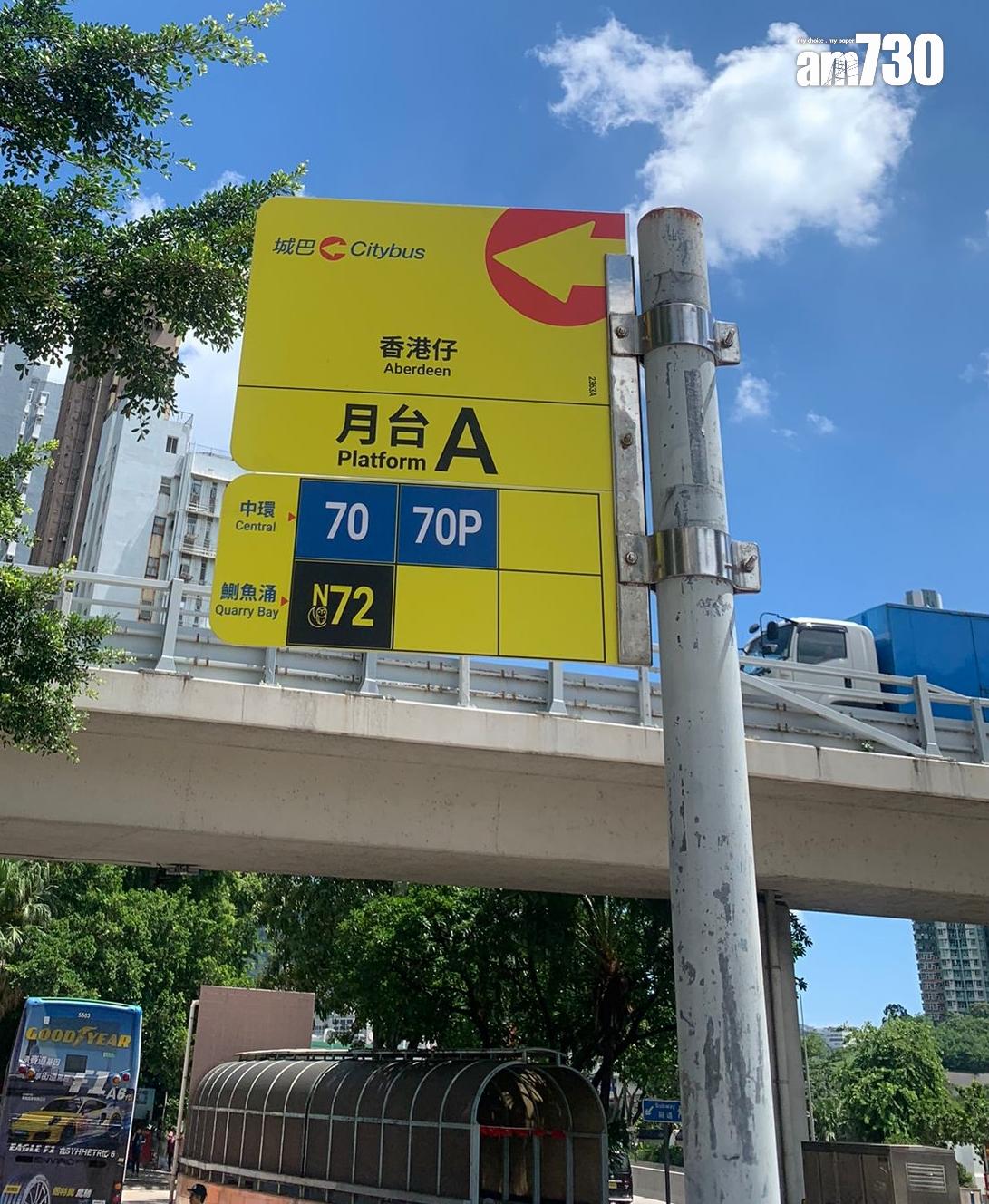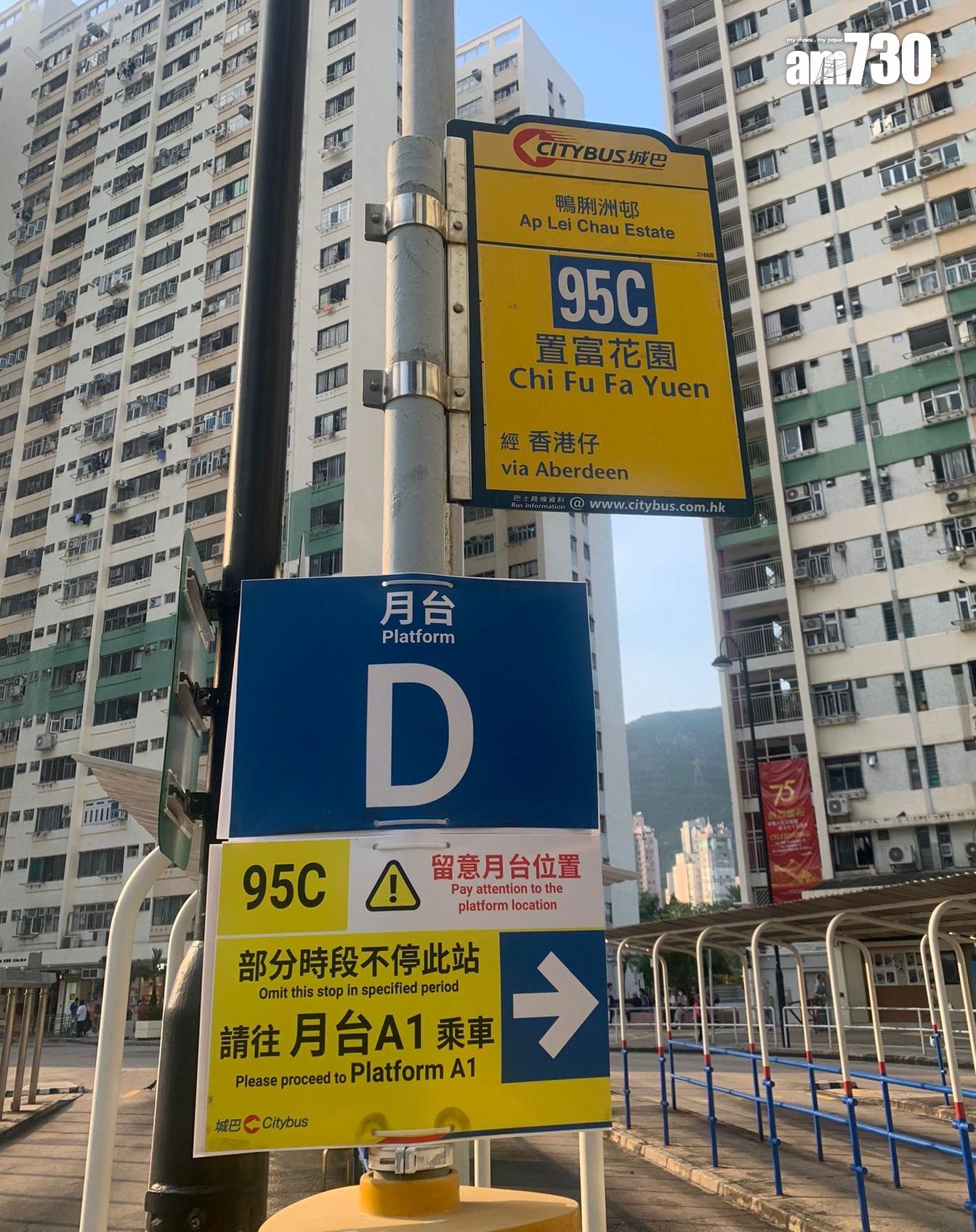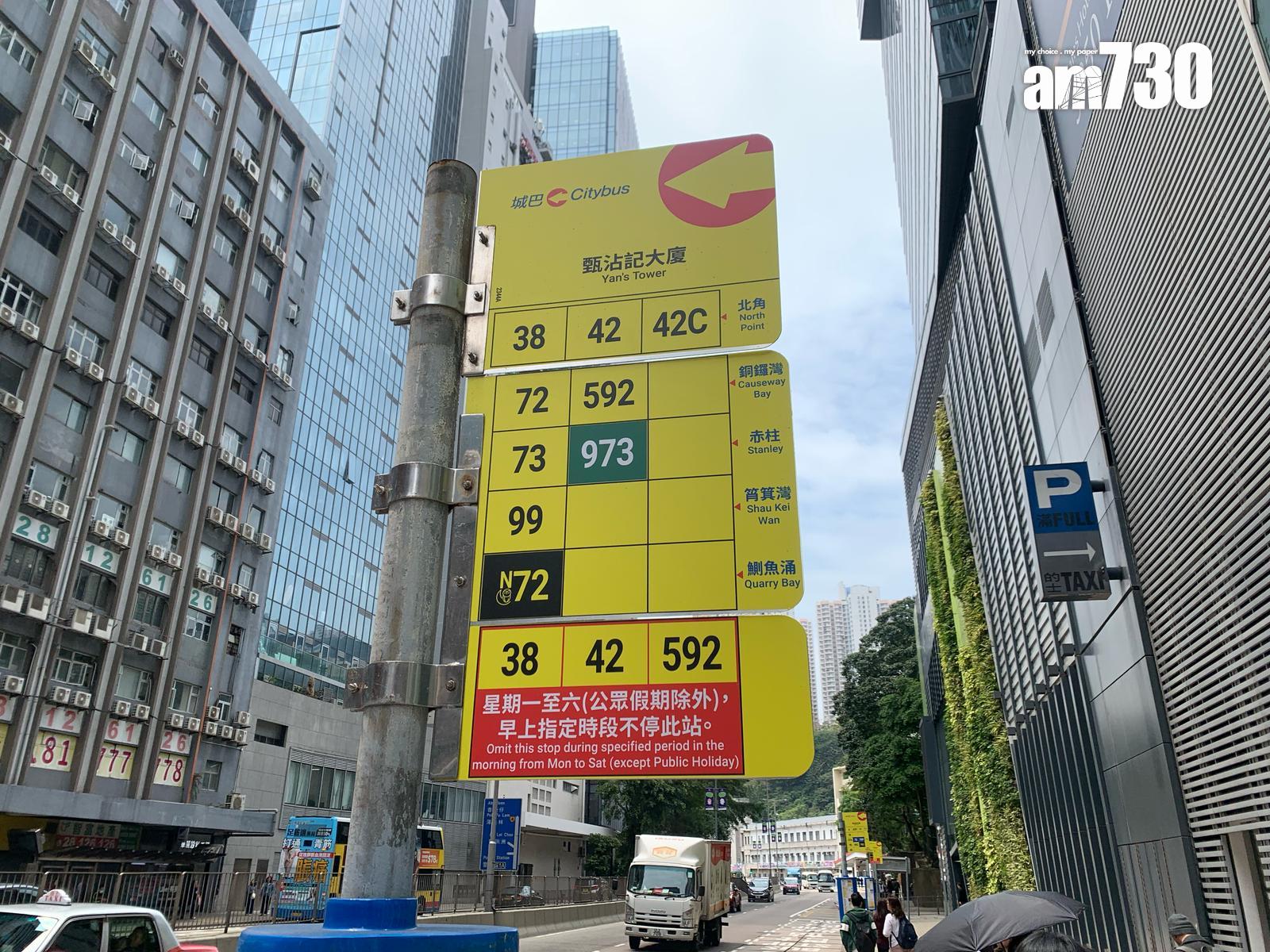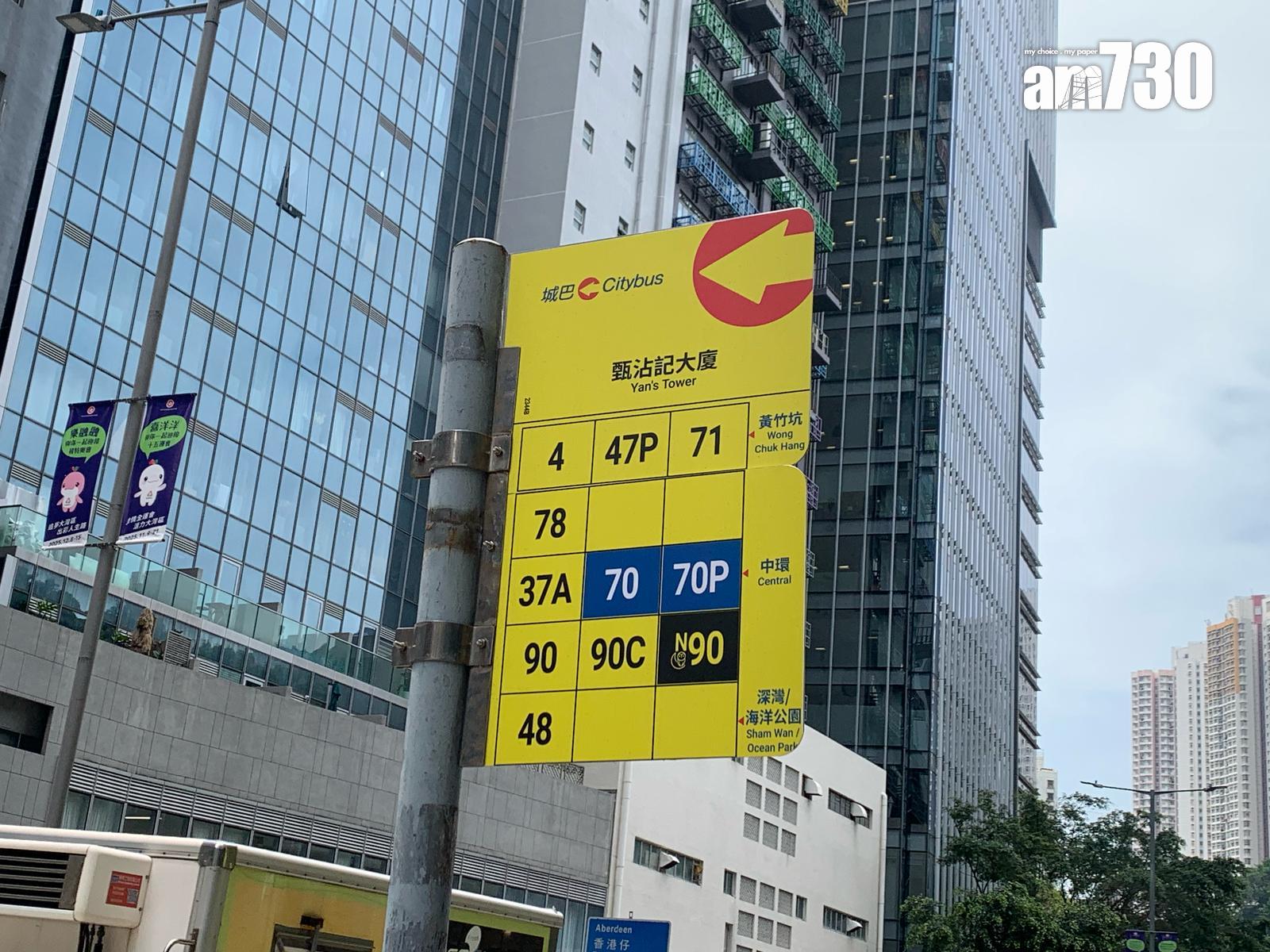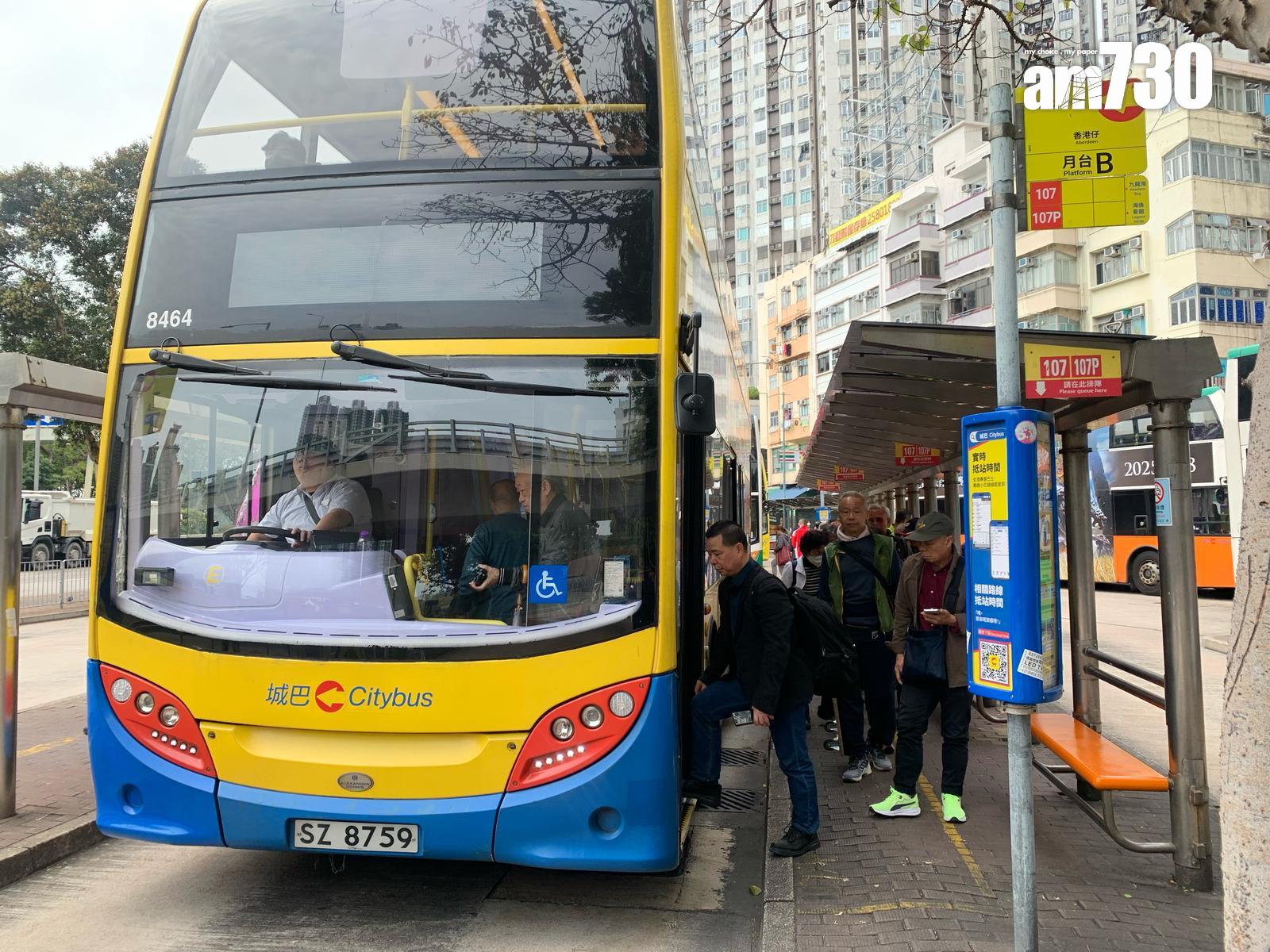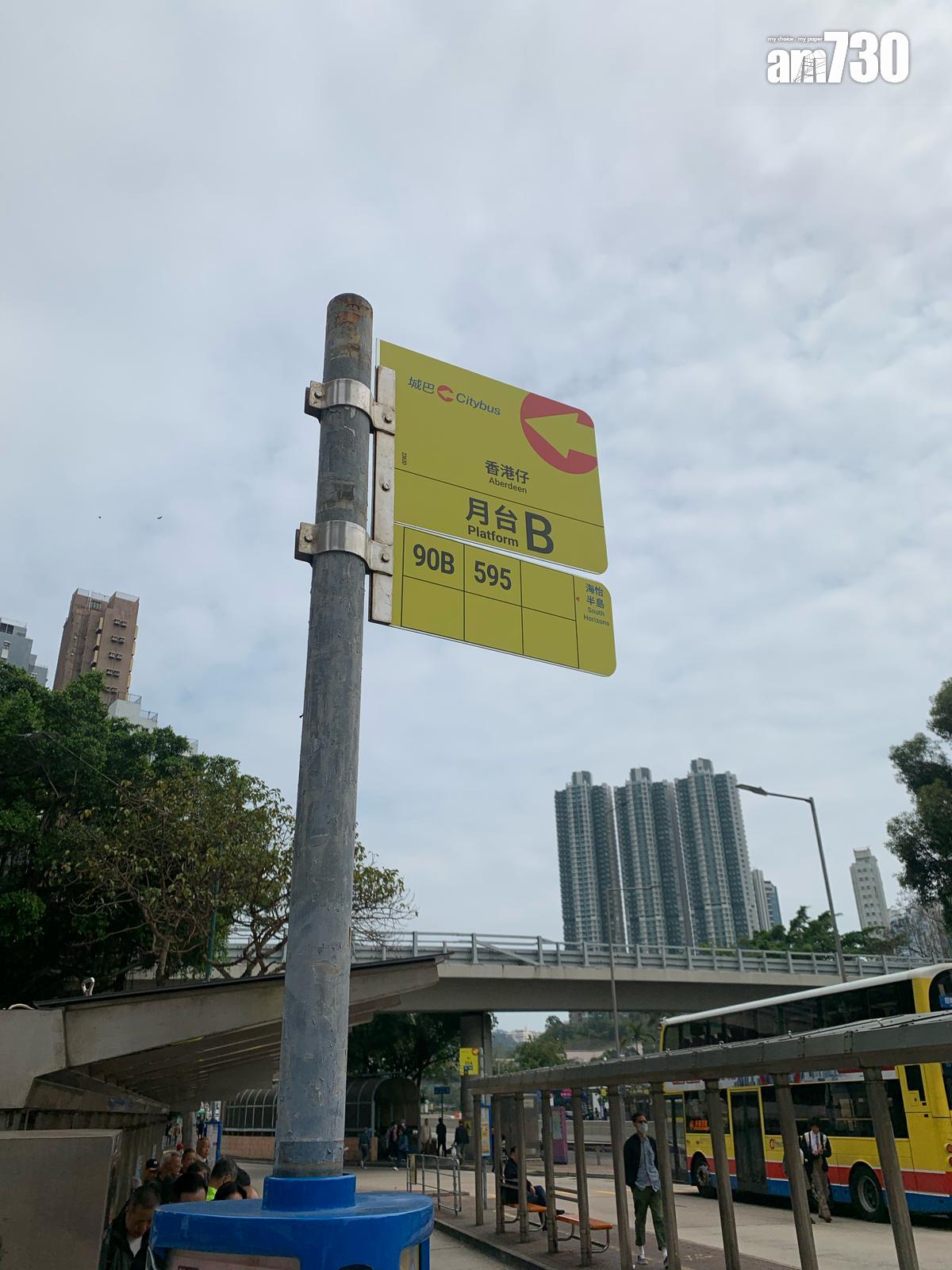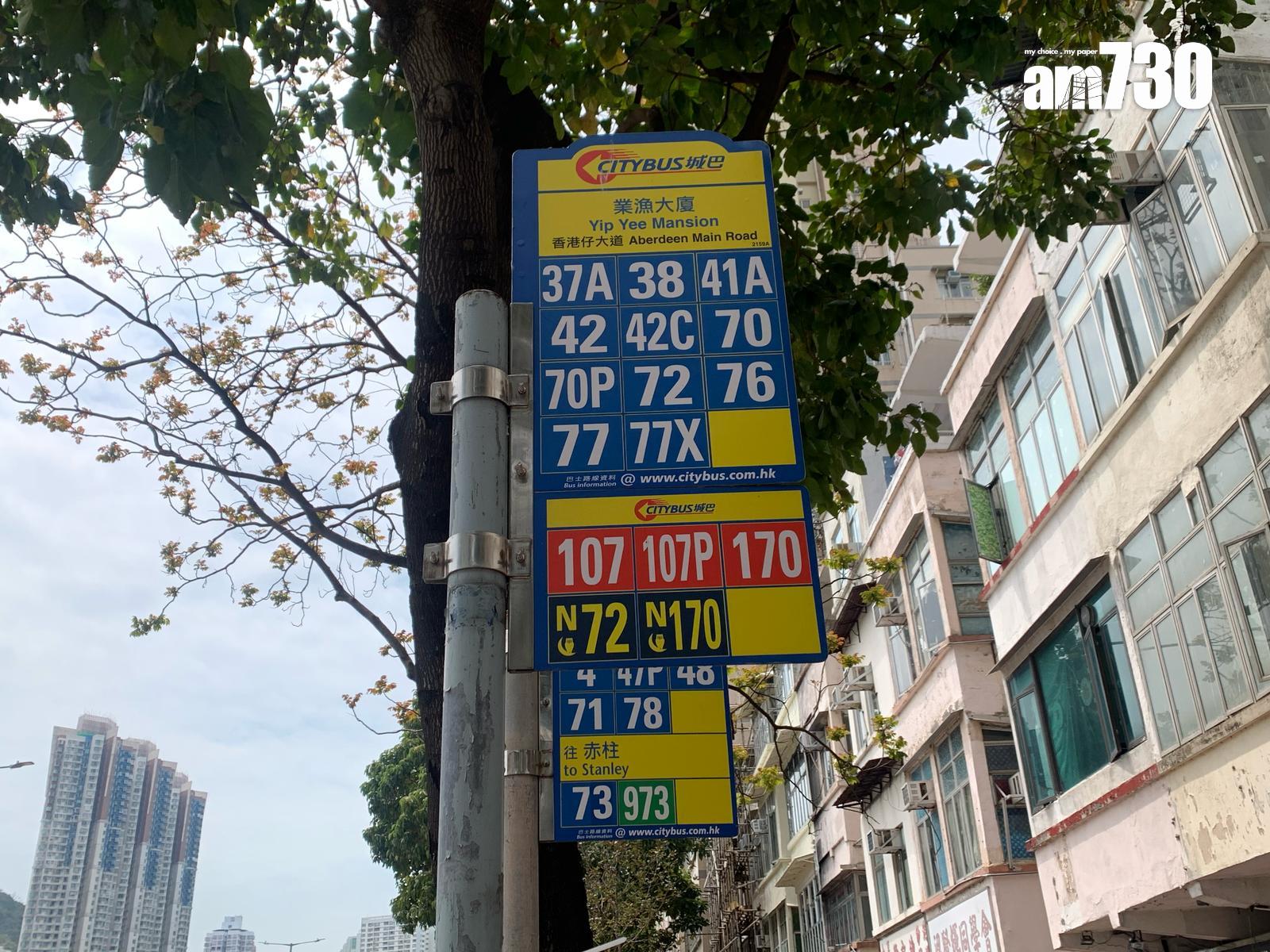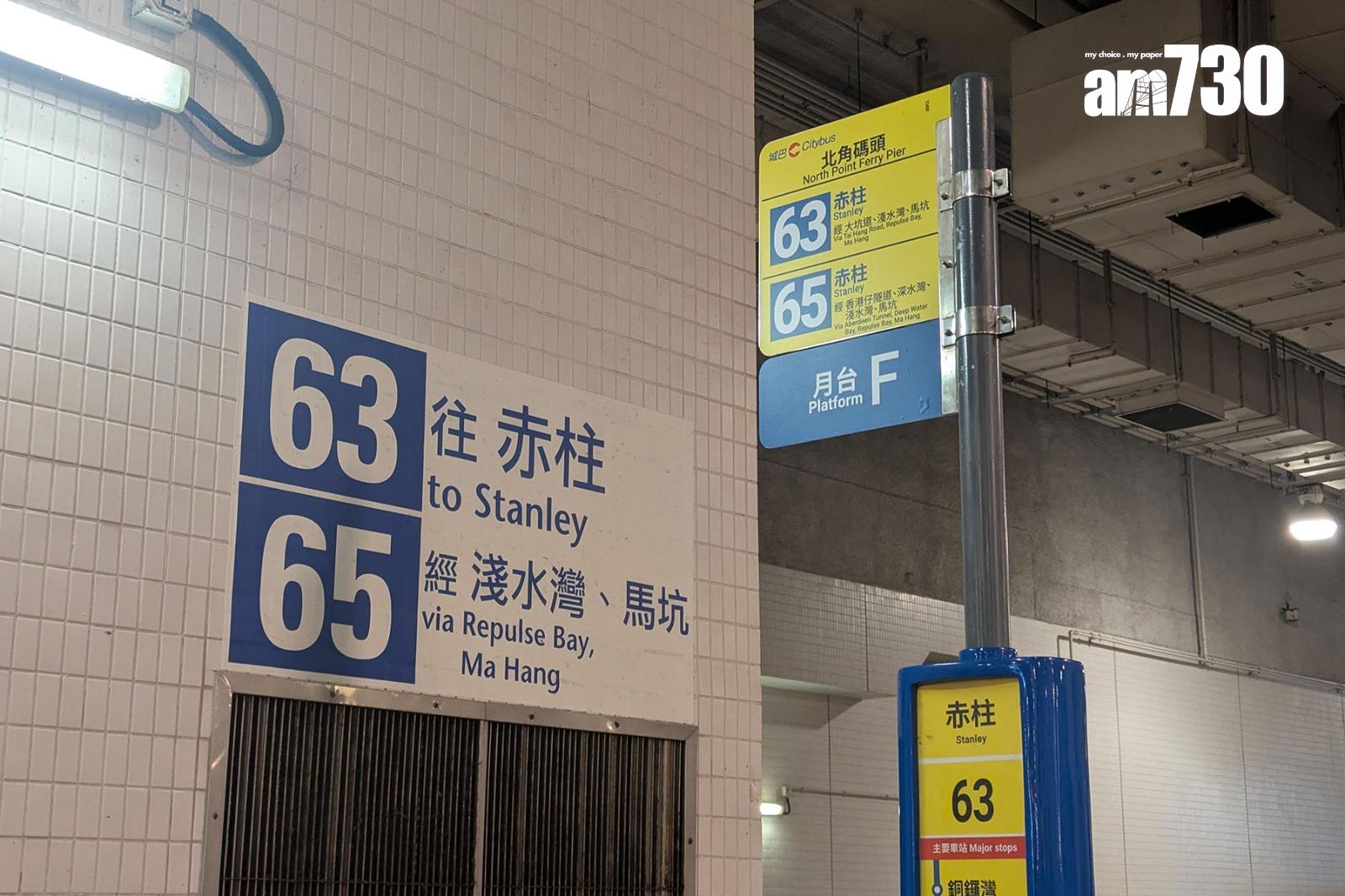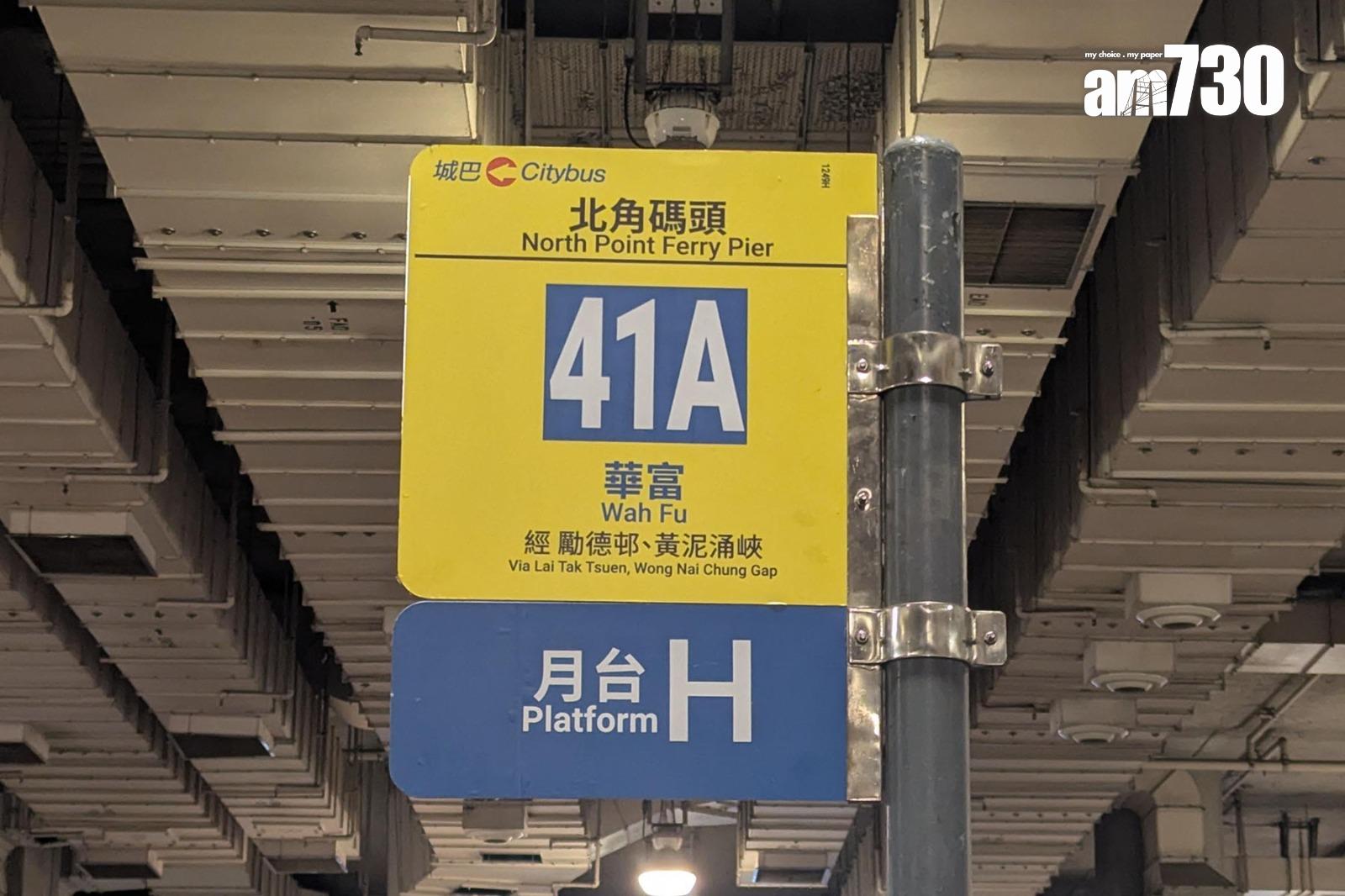
城巴更換新款巴士站牌 被批「似驗眼」後字體加大
在北角碼頭巴士總站,城巴已換上改良版新款站牌(讀者提供)
城巴去年與新巴合併後,為各區巴士站牌換上新設計,惟被指不清晰「似驗眼」影響乘客讀取路線資訊,失明人協進會接獲不少視障會員反映新設計對低視能人士做成不便,運輸署及後要求城巴改善。城巴回覆《am730》稱經諮詢相關關注團體後,已修訂巴士站牌設計,近日展開更換工程。
在北角碼頭巴士總站,城巴已換上改良版新款站牌,站牌沿用黃色設計,但對比上一款備受批評的款式,轉用較為粗身的字體,路線編號字體明顯加大,採用藍底白字粗字體,的地及途徑地點亦清晰地展示,月台編號分開擺放,不再出現月台編號比路線編號更大的設計。
城巴回覆《am730》稱自專營權合併以來,留意到乘客對巴士站牌設計有不同意見,公司持續與各持分者保持密切溝通,在諮詢相關關注團體後,城巴修訂巴士站牌設計,並於本月中旬起展開更換工程,新巴士站牌在字體大小及顏色等方面回應社會關切。
城巴為各區巴士站牌換上新設計,惟有乘客及網民均反映新站牌的路綫號碼比舊版縮細及出現「撞色」問題,難從遠方觀看,亦加了「月台」字眼更加混淆,批評設計倒退。(《am730》記者攝) 城巴為各區巴士站牌換上新設計,惟有乘客及網民均反映新站牌的路綫號碼比舊版縮細及出現「撞色」問題,難從遠方觀看,亦加了「月台」字眼更加混淆,批評設計倒退。(《am730》記者攝) 香港仔巴士總站已換上新站牌(《am730》記者攝) 城巴為各區巴士站牌換上新設計,惟有乘客及網民均反映新站牌的路綫號碼比舊版縮細及出現「撞色」問題,難從遠方觀看,亦加了「月台」字眼更加混淆,批評設計倒退。(《am730》記者攝) 有網民比較銅鑼灣希慎廣場新巴舊牌及城巴新站牌。(社交平台Threads) 城巴為各區巴士站牌換上新設計,惟有乘客及網民均反映新站牌的路綫號碼比舊版縮細及出現「撞色」問題,難從遠方觀看,亦加了「月台」字眼更加混淆,批評設計倒退。香港仔大道仍有巴士站使用舊站牌。(《am730》記者攝) 城巴為各區巴士站牌換上新設計,惟有乘客及網民均反映新站牌的路綫號碼比舊版縮細及出現「撞色」問題,難從遠方觀看,亦加了「月台」字眼更加混淆,批評設計倒退。(《am730》記者攝) 城巴舊版巴士站牌注重放大巴士號碼的設計(社交平台Threads) 鴨脷洲邨巴士總站站牌加了「月台」字眼(《am730》記者攝)
9成網民斥新不如舊 城巴小編曾稱「不如適應新事物」
城巴去年起巴士路線號碼牌換上新設計,有乘客及網民均反映新站牌的路綫號碼比舊版縮細及出現「撞色」問題,難從遠方觀看,批評設計倒退「睇到似驗眼咁辛苦」,社交平台Threads更有網民發起投票,結果93%均屬意舊款站牌,惟帖文引起城巴Threads官方帳號「小編」現身,留言回應「每個人考慮嘅點唔同啦!由設計到審批,到最後出來嘅結果,肯定經過多層考慮,一個設計亦不可能滿足曬所有人。咁既然改變唔到,與其執著好定唔好,不如慢慢適應新嘅事物囉!」
視障人士投訴  運輸署要求改善
香港失明人協進會3月向城巴發公開信,指巴士是不少視障人士的主要交通工具,去年城巴更新巴士路線號碼牌的設計後,該會接獲不少視障會員反映,指新設計對低視能人士做成不便。運輸署5月表示,自2023年7月相關專營權合併至今,共接獲14宗有關城巴新站牌設計的投訴,主要涉及字體較原有設計小,署方要求城巴作出改善。